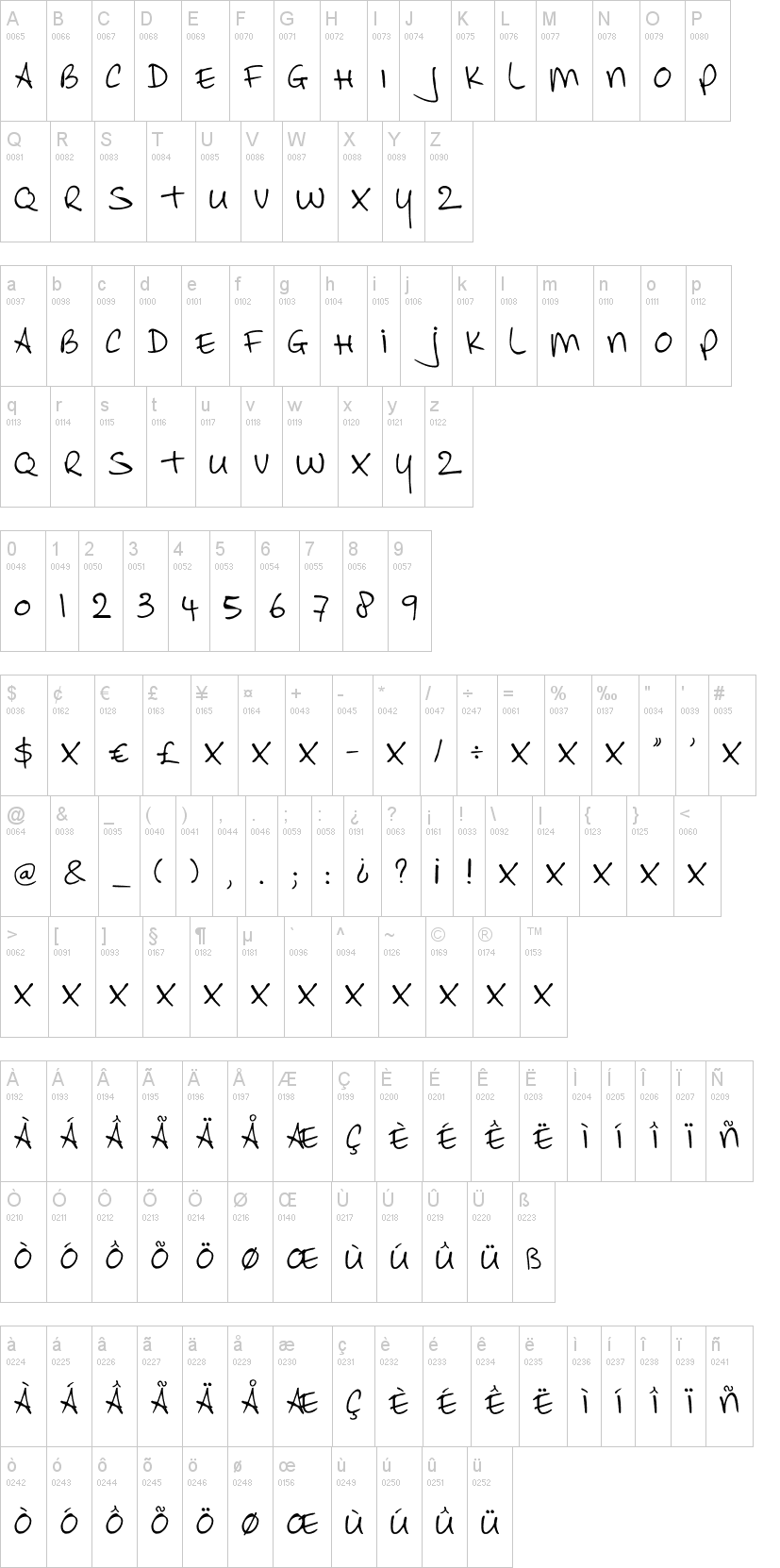
DK Allez Hop是一款由Dalton Maag设计的英文字体,它采用了自然的流动线条,给人一种温暖、亲切的感觉,是一款极具视觉冲击力的字体。它的字形比较宽松,在使用时可以增强文本的可读性,同时也可以提高文字的视觉效果。它的特色在于它具有非常细腻的细节,能够提升文字的外观,使文字更具有吸引力。内容介绍
DK Allez Hop是一款非常不错的手写艺术字体,具有很好的视觉感,适合于文化类的宣传设计、商业类品牌的广告和产品包装设计以及个性化文字排版等较多场景。